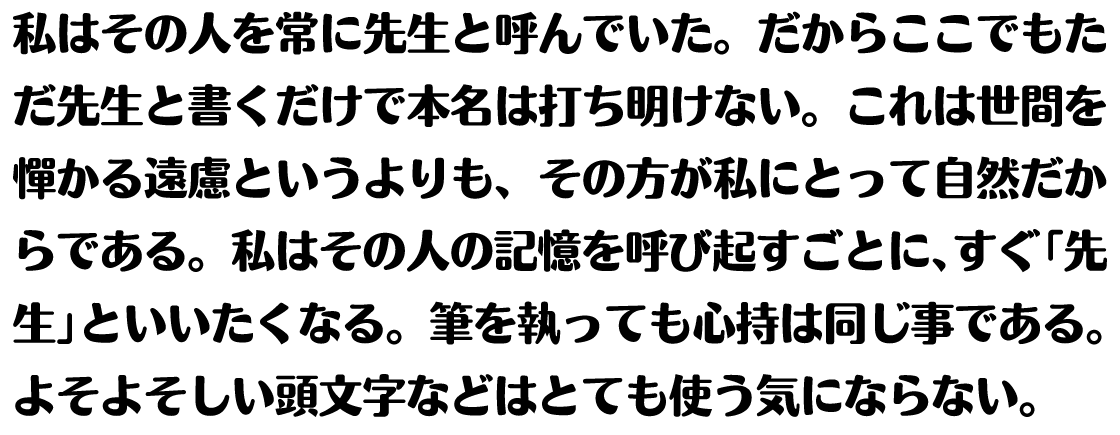
モトヤ丸アポロ
書体解説
モトヤ丸アポロは、スッキリとして明るいイメージが特徴のアポロから生まれた書体です。ハネ先や角を丸める事で柔らかさを表現しており、点の押さえや右ハライの終筆部分などは丸めず鋭角にすることでまろやかな中にもシャープさをかもし出しています。本文から見出しに使用可能なウエイトをラインナップして、より多彩な文章表現が可能になりました。1969年にタイプ活字として開発された「モトヤアポロ」は、半世紀近い時を経て書体づくりへの真摯な姿勢が引き継がれ「丸アポロファミリー」へと昇華を遂げました。